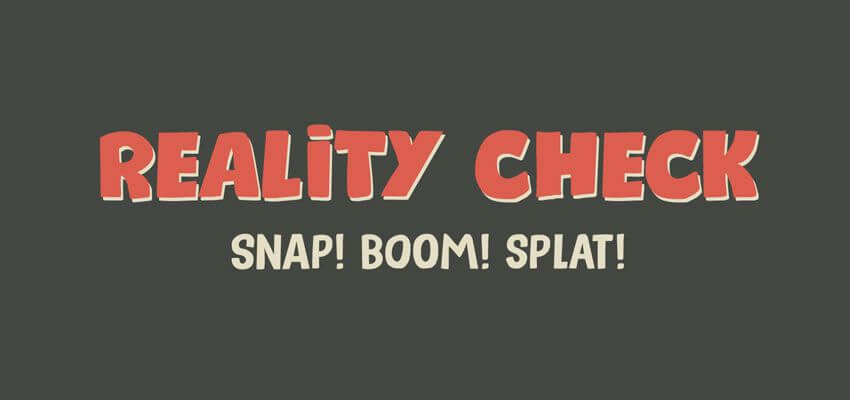
コミカルなマンガ調のデザインに活かせるアメコミ風フリーフォント20選 ポップでアメリカンな無料素材
漫画のフォントは、その漫画にとって違和感がないような自然なフォントの選択が必要です。けれども、思いきったフォントデザインのおかげでエッジの効いた表現をすることができます。このようなフォントは、ポスターデザインや見出しに使用するのに最適です。また、子ども向けの本を読みやすくするために使うこともできます。
長い間、漫画の雰囲気が求められるデザインにおいて、コミックサンズが利用されることが一般的でした。幸いなことに、現在ではその他の選択肢があります。あなたのデザインをひと工夫するために、高品質の漫画向けフリーフォントが使えます。この様なフォントは無料なものもあり、個人利用したり、ダウンロードをして商用利用できたりします。
Reality Check Comic Font
Reality Checkは漫画向けフォントです。個人利用は無料ですが、商用利用にはライセンスの購入が必要です。このフォントの特徴は、大文字と記号が立体的に描かれているところです。
Crime Fighter Comic Font
Crime Fighter fontは、非営利目的やインディーコミックに無料で使用できます。大文字、記号、数字が含まれており、2種類あります。
Hey Comic
このフォントは明るく、丸くて太めの文字に見えます。漫画だけでなく、子ども向けの本や誕生日の招待状などにも使用できます。Envato Elementsからダウンロードできます。
Billy Typeface
Billy fontは、個人利用できる現代的で丸みがあるフォントです。商業利用の場合は、ライセンスを購入する必要があります。フォントには、大文字、小文字、数字、記号が含まれます。
VTC Letterer Pro Font
VTC Letterer Proは、漫画だけでなく目立つフォントが必要な時にも適している全て大文字のフォントです。個人、商業利用は無料です。
Back Issues Comic Font
大胆なフォントです。大文字、記号、数字があります。インディーズや非営利目的で使用できます。
Kalam on Google Font
Kalam fontはGoogle Fontsからダウンロードでき、個人利用や商業利用ができます。デーヴァナーガリー文字とラテン文字をカバーします。
Rocky Type Font
Rocky fontは、無料でダウンロードでき、個人利用や商業利用ができます。大文字のフォントです。岩で作られたように見える独特のフォントです。
もし、デザインに特別な雰囲気を加えたいなと思ったときは、これらのフォントを使ってみてください。どれも大胆で注目を集めるので、現代的でエッジの効いたデザインに最適です。ここで紹介したフォントは無料でダウンロードできて、商業利用できるものもあるので、よろしければお気に入りに登録して利用してください。